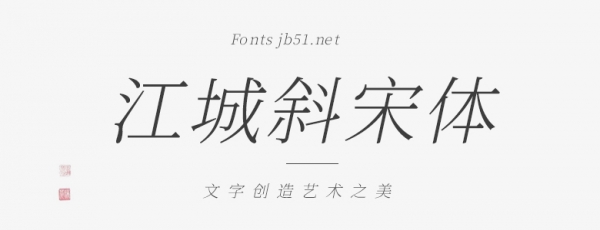
江城斜宋體這款字體是基于思源黑體進(jìn)行改造而成,江城斜宋體傾斜12度。傾斜的字體能帶給人力量感,速度感。在PS和AI中要把一款字體進(jìn)行傾斜還是一件比較簡單的事情,但是在某些軟件中,要制作傾斜的字體卻并不是那么簡單的事情。比如在PPT中一鍵傾斜就可以完成的事情,在Keynote中往往變得很復(fù)雜 ,因為在Keynote不支持中文傾斜字。